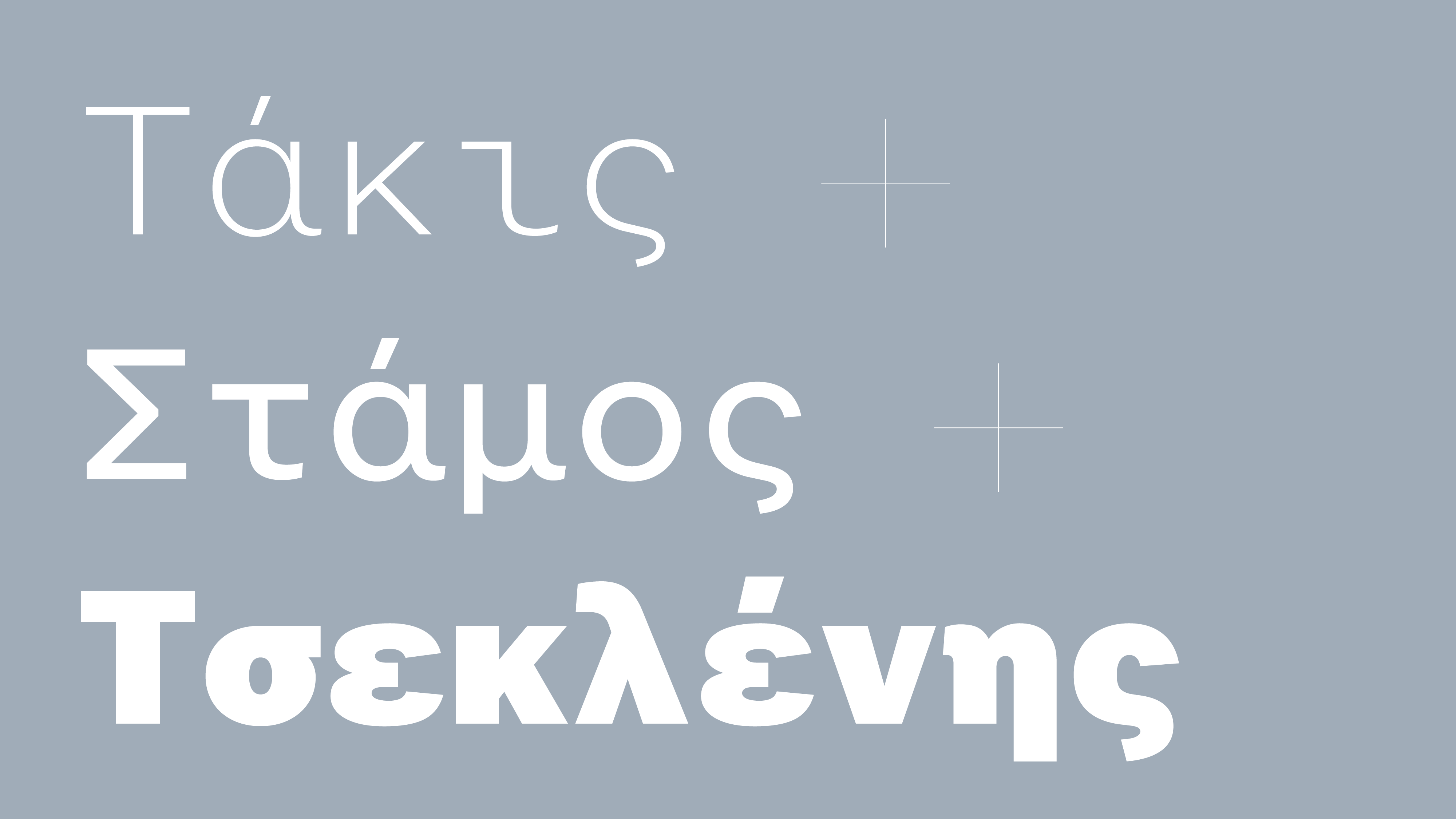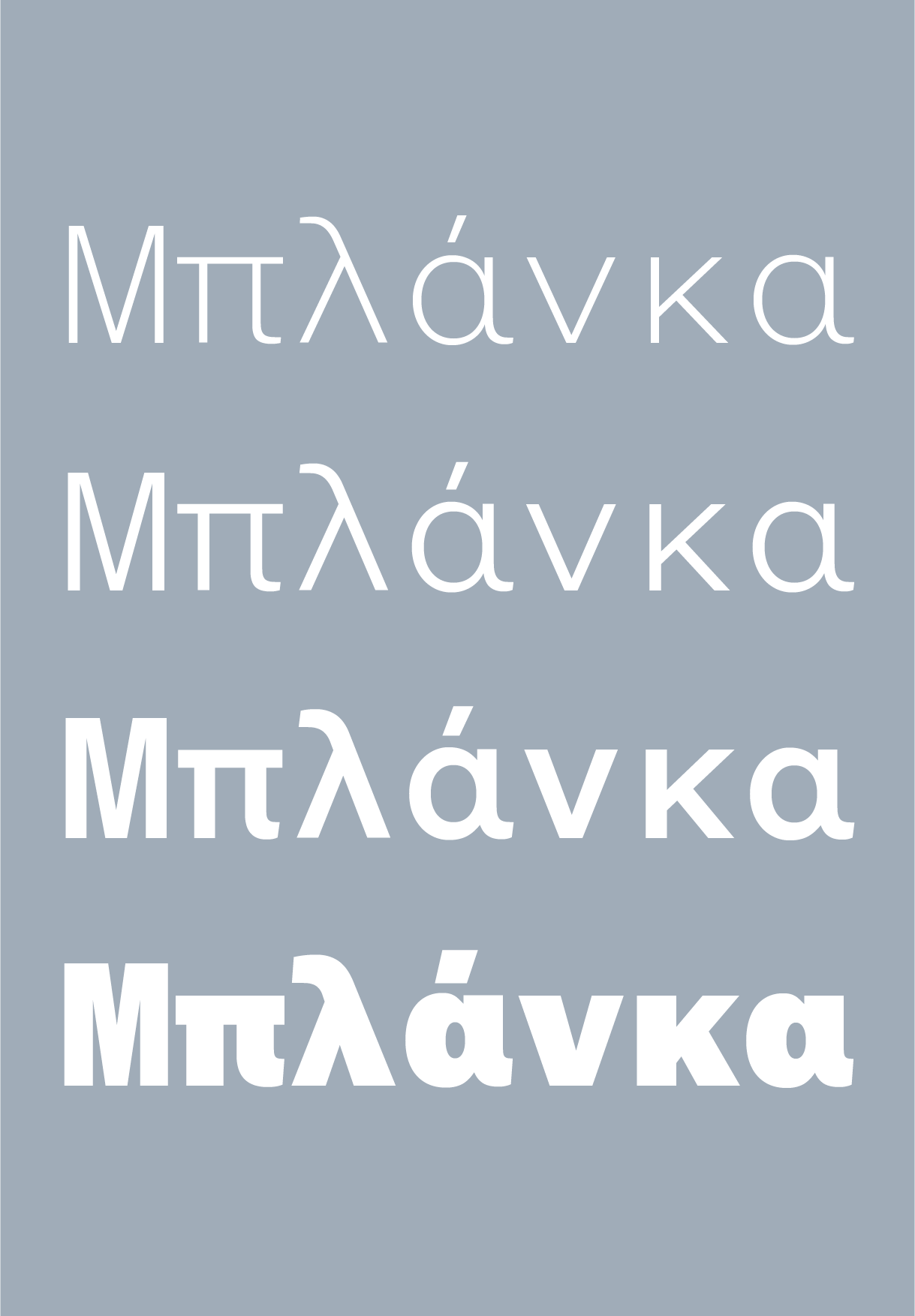
F37 Blanka Mono Greek Font Sampler
Η Blanka είναι η αντίληψη της F37 για ένα καθαρό, κλασικό ελβετικό sans. Ιδανικό για αντιγραφή σώματος, είναι οικονομικό, λειτουργικό και πολύ ευανάγνωστο σε μικρά μεγέθη.